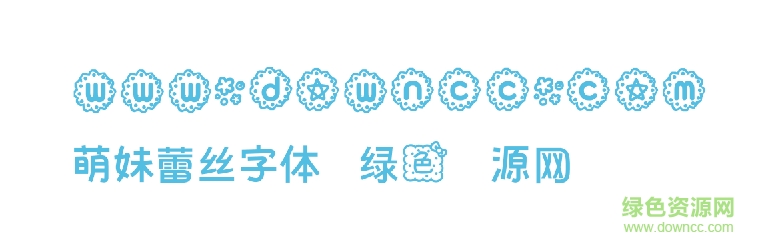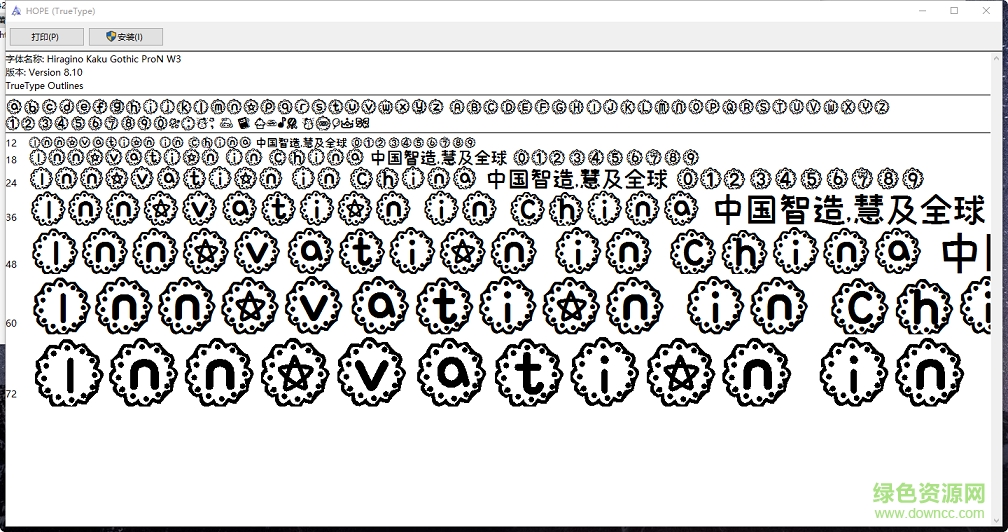
萌妹蕾絲字體
蕾絲字體是一款適合女生的字體,獨(dú)具一格的設(shè)計(jì)讓人印象深刻。歡迎需要的用戶來(lái)綠色資源網(wǎng)下載使用。
蕾絲介紹
一款非??蓯?ài)的字體,適合設(shè)計(jì)行業(yè)。
蕾絲字體
蕾絲字體測(cè)評(píng)
蕾絲字體筆畫(huà)不拘一格,給人清新脫俗的感覺(jué),十分好看迷人,綠色資源網(wǎng)為您提供綠色免費(fèi)的蕾絲字體下載!